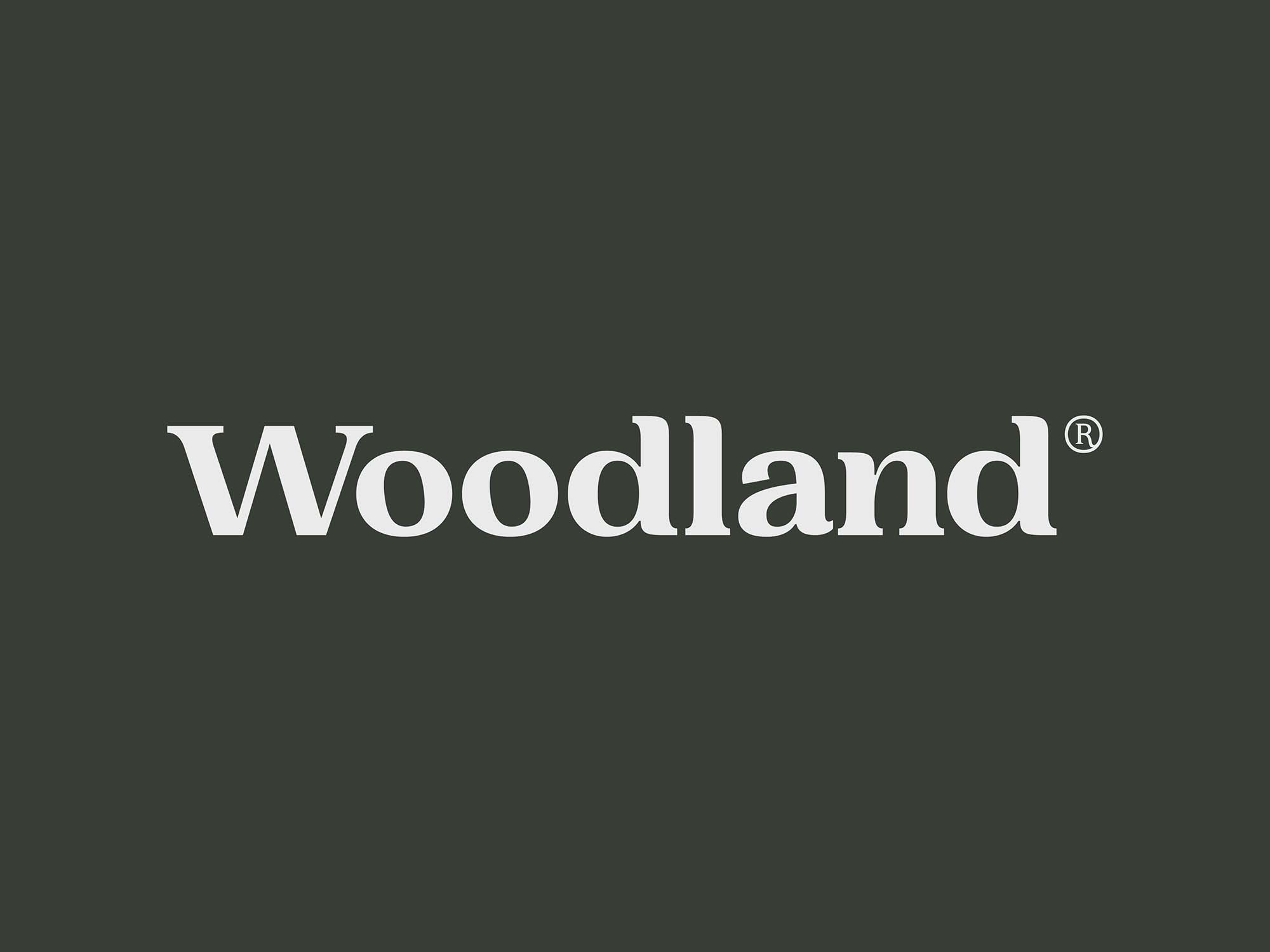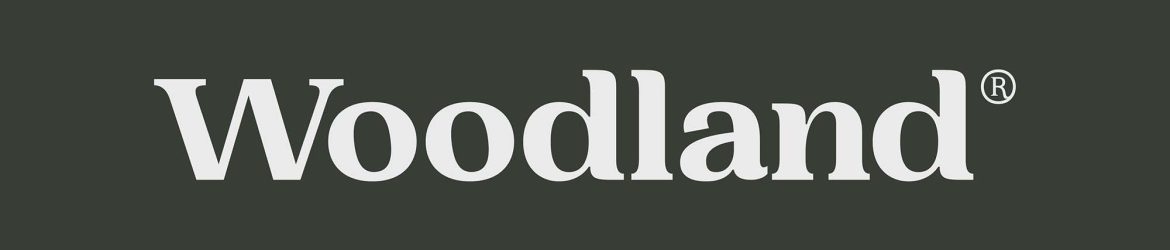
A nova fonte de tipo ‘Woodland Serif Typeface’ é uma criação que vai revolucionar a maneira como você trabalha com mockups em seu design. Inovadora e sofisticada, esta fonte é perfeita para designers que valorizam o equilíbrio entre elegância e simplicidade. O design arredondado e o padrão de serif proporcionam um toque de elegância ao seu trabalho, tornando-a uma opção ótima para projetos de revistas, flyers e qualquer outro projeto gráfico que exigir um acabamento elegante. Com sua beleza natural e sua versatilidade, esta fonte é ideal para quem procura um recurso que pode revolucionar seus designs. Seja você um designer de nivel, ou um amante do design, esta fonte oferece um novo nível de sofisticação e criatividade para seus projetos.